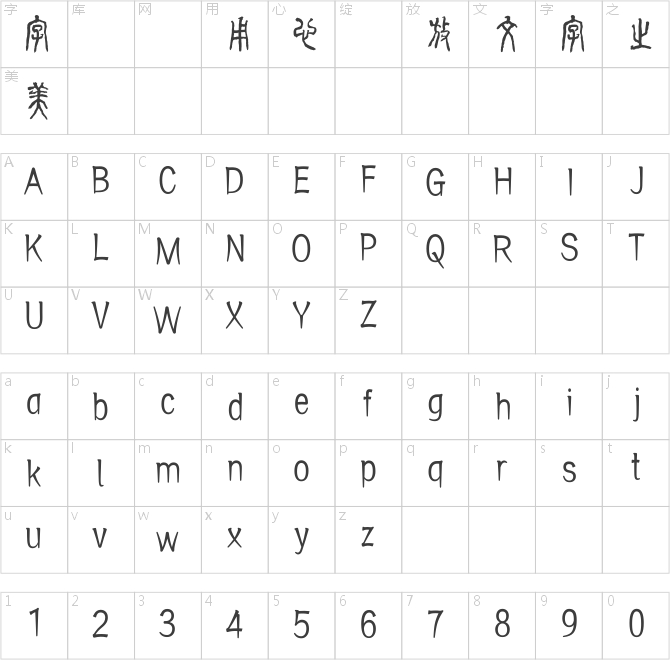
方正字跡--顧建平酷篆體,由上海交大文化創(chuàng)意獎(jiǎng)、新加坡杰出貢獻(xiàn)獎(jiǎng)、文化藝術(shù)獎(jiǎng)得主,文字學(xué)家、書(shū)法家顧建平所創(chuàng)。如菩薩亦男亦女造型,現(xiàn)代中性跨界打扮,酷篆運(yùn)用古老東方中庸智慧與現(xiàn)代審美中性風(fēng)尚,突破傳統(tǒng)小篆婉約柔美局限,剛?cè)嵯酀?jì)、拙秀并用,獨(dú)創(chuàng)雅俗共賞、男女皆宜的炫酷篆書(shū)??嶙貏e適合影視、游戲、廣告、包裝等用字。